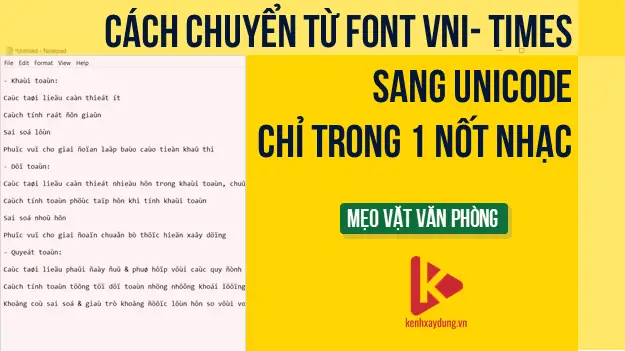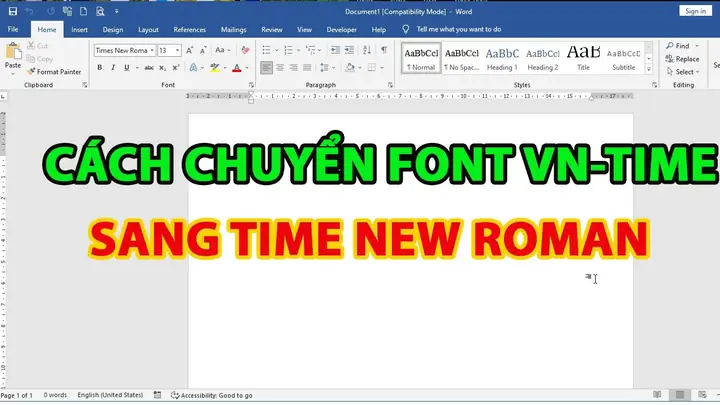
Trong môi trường soạn thảo văn bản, việc chuyển đổi giữa các kiểu font chữ là điều không thể tránh khỏi, đặc biệt là khi làm việc với các tài liệu học thuật, văn bản hành chính hoặc các bài viết cần tuân thủ định dạng chuẩn. Một trong những thách thức phổ biến mà nhiều người dùng gặp phải, đặc biệt là những ai đang xử lý các tài liệu cũ hoặc văn bản được soạn thảo bằng bộ gõ tiếng Việt như Unikey, là việc chuyển đổi font từ VNI Times sang Time New Roman. VNI Times là một font chữ phổ biến trong quá khứ, được thiết kế riêng để hỗ trợ gõ tiếng Việt theo kiểu VNI, trong khi Time New Roman là font chữ chuẩn quốc tế, được yêu cầu trong hầu hết các văn bản học thuật và hành chính hiện nay.
Việc chuyển đổi font không chỉ đơn thuần là thay đổi kiểu chữ; nó còn liên quan đến việc xử lý bảng mã ký tự, đảm bảo rằng các dấu tiếng Việt vẫn được hiển thị chính xác sau khi chuyển đổi. Nếu không thực hiện đúng cách, văn bản có thể bị lỗi font, các dấu tiếng Việt bị sai lệch, hoặc nội dung hoàn toàn không đọc được. Điều này gây ra không ít khó khăn, đặc biệt là với những người không am hiểu nhiều về kỹ thuật xử lý văn bản.
Bài viết này sẽ cung cấp cho bạn một hướng dẫn chi tiết, từng bước một, để chuyển đổi font từ VNI Times sang Time New Roman một cách nhanh chóng và hiệu quả. Chúng tôi sẽ trình bày các phương pháp khác nhau, từ việc sử dụng các công cụ trực tuyến miễn phí cho đến các phần mềm chuyên dụng, cũng như hướng dẫn chuyển đổi thủ công bằng Microsoft Word. Mỗi phương pháp đều có ưu và nhược điểm riêng, phù hợp với từng nhu cầu và mức độ phức tạp của tài liệu. Dù bạn là người mới bắt đầu hay đã có kinh nghiệm, bài viết này sẽ giúp bạn tìm ra giải pháp phù hợp nhất và hoàn thành việc chuyển đổi một cách dễ dàng.
Tóm tắt các bước chuyển đổi font VNI Times sang Time New Roman
- Chọn phương pháp chuyển đổi: Sử dụng công cụ trực tuyến (Convert Text, VNI Convert), phần mềm chuyên dụng (Unikey, Vietkey), hoặc chuyển đổi thủ công trong Word.
- Thực hiện chuyển đổi: Sao chép nội dung, dán vào công cụ chuyển đổi, chọn bảng mã đầu vào (VNI) và đầu ra (Unicode), sau đó tải về file đã chuyển đổi.
- Kiểm tra và hiệu chỉnh: Mở file kết quả, kiểm tra lỗi font, định dạng, và hiệu chỉnh nếu cần.
Tìm hiểu về font VNI Times và Time New Roman
Khái niệm về font VNI Times
Font VNI Times là một trong những font chữ phổ biến nhất được sử dụng trong môi trường soạn thảo văn bản tiếng Việt vào những năm 1990 và đầu 2000. Font này được phát triển bởi công ty VNI (Vietnamese Network Inc.) nhằm hỗ trợ việc gõ tiếng Việt theo kiểu VNI, một trong những phương pháp gõ tiếng Việt phổ biến nhất tại Việt Nam. VNI Times là phiên bản mở rộng của font Times New Roman, được bổ sung các ký tự đặc biệt để hiển thị các dấu tiếng Việt như huyền, sắc, hỏi, ngã, nặng và các chữ cái có dấu như ă, â, đ, ê, ô, ơ, ư.
VNI Times sử dụng bảng mã VNI, một bảng mã dựa trên bảng mã ASCII nhưng được mở rộng để chứa các ký tự tiếng Việt. Khi người dùng gõ tiếng Việt bằng bộ gõ VNI, các ký tự được nhập vào máy tính dưới dạng mã VNI, và font VNI Times có nhiệm vụ hiển thị các ký tự này một cách chính xác trên màn hình. Tuy nhiên, do VNI Times là một font dựa trên bảng mã riêng biệt, nó không tương thích với các hệ thống sử dụng bảng mã Unicode, vốn là chuẩn quốc tế hiện nay.
Khái niệm về font Time New Roman
Time New Roman, hay còn gọi là Times New Roman, là một font chữ serif được thiết kế vào năm 1931 bởi Stanley Morison và Victor Lardent. Font này được phát triển để sử dụng trong tờ báo The Times của Anh, với mục tiêu tạo ra một font chữ dễ đọc, thanh lịch và tiết kiệm giấy. Times New Roman nhanh chóng trở thành một trong những font chữ phổ biến nhất trên thế giới, đặc biệt là trong các tài liệu học thuật, văn bản hành chính, và các ấn phẩm chính thức.
Times New Roman sử dụng bảng mã Unicode, chuẩn mã hóa ký tự quốc tế được hỗ trợ rộng rãi trên tất cả các hệ điều hành và phần mềm hiện đại. Điều này có nghĩa là bất kỳ văn bản nào được soạn thảo bằng Times New Roman đều có thể được hiển thị chính xác trên mọi thiết bị, bất kể hệ điều hành hay phần mềm được sử dụng. Đây là lý do tại sao Times New Roman thường là font chữ được yêu cầu trong các bài luận, báo cáo, và các tài liệu chính thức.
Sự khác biệt giữa VNI Times và Time New Roman
Sự khác biệt lớn nhất giữa VNI Times và Time New Roman nằm ở bảng mã và cách xử lý các ký tự tiếng Việt. VNI Times sử dụng bảng mã VNI, một bảng mã dựa trên ASCII nhưng được mở rộng để chứa các ký tự tiếng Việt. Trong khi đó, Time New Roman sử dụng bảng mã Unicode, chuẩn mã hóa ký tự quốc tế được hỗ trợ rộng rãi trên tất cả các hệ điều hành và phần mềm hiện đại.
Một điểm khác biệt quan trọng khác là về mặt thiết kế. Mặc dù VNI Times được phát triển dựa trên nền tảng của Times New Roman, nhưng do phải bổ sung các ký tự đặc biệt để hỗ trợ tiếng Việt, nên có một số khác biệt nhỏ về hình dạng và khoảng cách giữa các ký tự. Điều này có thể ảnh hưởng đến cách hiển thị của văn bản, đặc biệt là khi chuyển đổi từ VNI Times sang Time New Roman.
Chuyển đổi bằng công cụ trực tuyến là nhanh chóng và tiện lợi, nhưng có thể không xử lý được các định dạng văn bản phức tạp. Chuyển đổi bằng phần mềm chuyên dụng có khả năng xử lý các định dạng văn bản phức tạp và hỗ trợ chuyển đổi hàng loạt, nhưng đòi hỏi người dùng phải có kiến thức kỹ thuật. Chuyển đổi thủ công trong Microsoft Word cho phép kiểm soát chi tiết quá trình chuyển đổi, nhưng